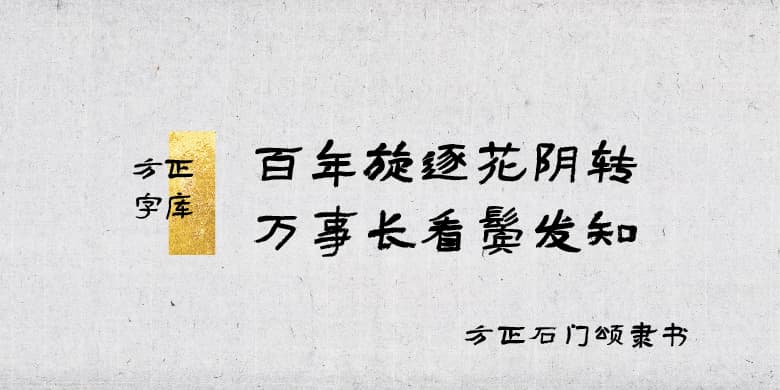
方正石门颂隶书
关于石门颂:
石门颂全称为《汉故司隶校尉犍为杨君颂》,是东汉建和二年(148年)由当时汉中太守王升撰文、书佐王戎书丹,刻于石门内壁西侧的一方隶书摩崖石刻。记载歌颂东汉汉顺帝时的司隶校尉杨孟文“数上奏请”修复褒斜道的事迹。
字体特征:
以《石门颂》为临创开发依据,结体洒落有致,纵横劲拔,流露出天真、飘逸的新奇之趣。
应用场景:
临创者:匡青海